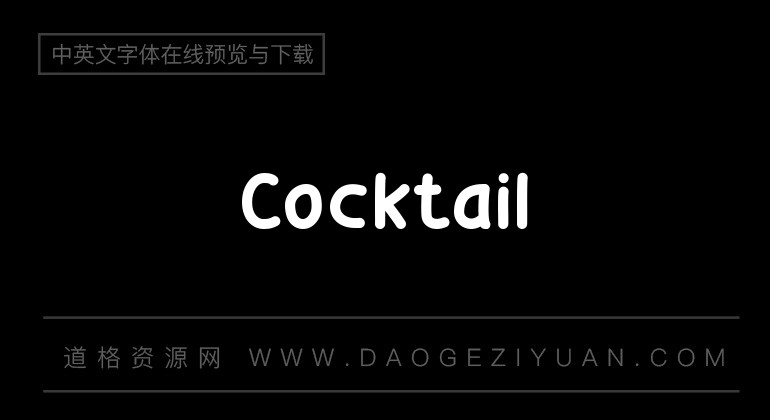
Cocktail
Cocktail 字体是一种拥有良好视觉效果的字体,它的设计具有简洁、优雅的风格,适合用于宣传海报、商业广告、网页设计等场景。Cocktail 字体的字形特点是细腻、精致,字体优雅,笔画细腻,字间距紧凑,文字效果精致,适合用于宣传海报、商业广告、网页设计等场景。
Cocktail是一款非常不错的手写艺术字体,具有很好的视觉感,适合于文化类的宣传设计、商业类品牌的广告和产品包装设计以及个性化文字排版等较多场景。